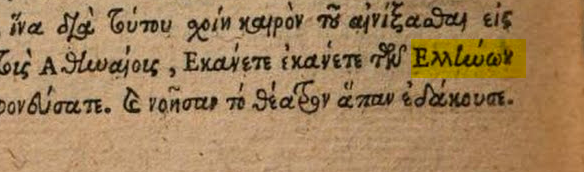
Wo gibt’s denn sowas: Tonos über Ny gesetzt?
Gott grüß Kunst! Kurze Frage an alle, die sich auch ein wenig mit altsprachlicher Druck-Geschichte auskennen: Ich habe hier zwei Beispiele, in denen – wie mir scheint – seltsamerweise der Tonos über dem Ny gesetzt wurde. Was hat es damit auf sich? Korrekt muß der Tonos über dem Eta stehen. Hat jemand dafür eine Erklärung oder Vermutung?
Beispiel No.1, Isocratis orationes et epistolæ, Quelle: https://books.google.de/books?id=mFBoAAAAcAAJ&pg=RA1-PA378#v=onepage&q&f=false (Papierseite 378, ziemlich ganz unten auf der Seite)
Beispiel No.2, Scaligers De caussis linguae Latinae: Quelle: https://books.google.de/books?id=MVw8AAAAcAAJ&pg=PT82 (Papierseite 52, etwa in der Mitte der Seite)
Ich würde die Verschiebung des Akuts so erklären, dass da durch die Oberlänge vom umgedrehten η über diesem kein Platz mehr ist, dieser nach rechts gerückt wird und über dem ν zu stehen kommt.
Ich habe zwar mit Griechisch nicht so viel Erfahrungen, aber so selten scheint es auch nicht gewesen zu sein, dass bei Abbreviaturen die Diakritika verschoben werden, siehe z.B. im Faulmann bei ἐπο, wo durch die Verbindung der Spiritus schlussendlich über dem ο steht.
Grüß dich crB, freue mich über Deinen Beitrag. Ja, etwas ähnliches habe ich auch vermutet, zumal es ja in beiden Drucken systematisch und absichtlich so gesetzt zu sein scheint. Meine Vermutung war: Der Setzer hätte den Akut zwar noch über dem Eta reinquetschen können, er wäre dann aber so dicht neben der Oberlänge des Etas, daß die Druckerschwärze von Oberlänge und Akut auf dem Papier zu einem einzigen unschönen schwarzen Fleck verlaufen wäre. Also im Grunde das gleiche Argument was du schon genannt hast!
Wobei zu vermuten ist, dass diese „Änderung“ nicht erst vom Setzer vorgenommen hatte. Die frühen Drucke orientierten sich stets stark an der Handschrift; die Verbindung wurde von der Handschrift übernommen, wo auch aus Zeitgründen der Akut einfach „irgendwo über die kurzen Bögen“ geschrieben wurde. Diese Verbindung wurde dann auf eine Letter übertragen, sodass der Setzer vermutlich – selbst wenn er gewollt hätte – nur diese ήν-Variante hätte setzen können, da sich der Akut bereits mit auf der Letter befand. Dies geht einher mit der Auffassung der Ligatur als Eiinzelzeichen, die sich dann verselbstständigen kann, wie es etwa bei den deutschen Umlauten geschehen ist, die ja auch im Alltag nur noch bedingt als Ligatur aufgefasst werden.
Hallo crB! Ich habe jetzt auch noch eine Antwort von einem Griechisch-Experten erhalten, und der sagt etwas ähnliches, nämlich daß es sich (so meintest Du auch wenn ich deinen richtig verstanden habe?) um eine ην-Ligatur handelt und der Akut über der Ligatur positioniert ist, nicht über dem Ny als Einzelletter. Nun, aus ästhetischen Gründen könnte man kritisch vielleicht anmerken, daß der Akut etwas weit nach rechts gerutscht ist auf der Ligatur, nicht wahr? Daher kam ja erst die Verwirrung zustande. Wäre er mittig über der Ligatur, hätte ich wohl auch die Ligatur auf Anhiebt als Ligatur erkannt.
(so meintest Du auch wenn ich deinen richtig verstanden habe?)
So meinte ich :nicken:und es freut mich, dass meine Theorie bestätigt wurde. Und dass so ein Akzent verrutscht, passiert beim  Schreiben schnell und war daher wahrscheinlich in vielen Handschriften der Fall, weshalb es dann als „übliche Variante“ in den Druck übernommen wurde.
Das erklärt dann auch, warum dieser griechische Satz so extrem nach Handschrift aussieht. Da finden dich, im Vergleich zum modernen Satz oder den lateinischen Buchstaben hier so gut wie keine klar abgesetzte Buchstaben, sondern es schaut für mich wie eine aus zig Ligaturen gesetzte Silbenschrift aus. Gibt es so etwas eigentlich digital??? Ohne OpenType-Ligaturen wohl kaum handhabbar, denke ich
Oha, Extremligaturing!
Interessant wäre ja dann, wie hier LibreOffice mit klar kommt, oder?
either in the form of OpenType features or in the form of glyphs.
either/or??? das sind doch immer Glyphen, die dann über OpenType-Features abgerufen werden. Hmm?
In meiner Abschrift benutze ich tatsächlich auch den Font "Grecs Du Roi", um dem Original-Druck/Schriftbild zu getreu wie möglich nahezukommen.